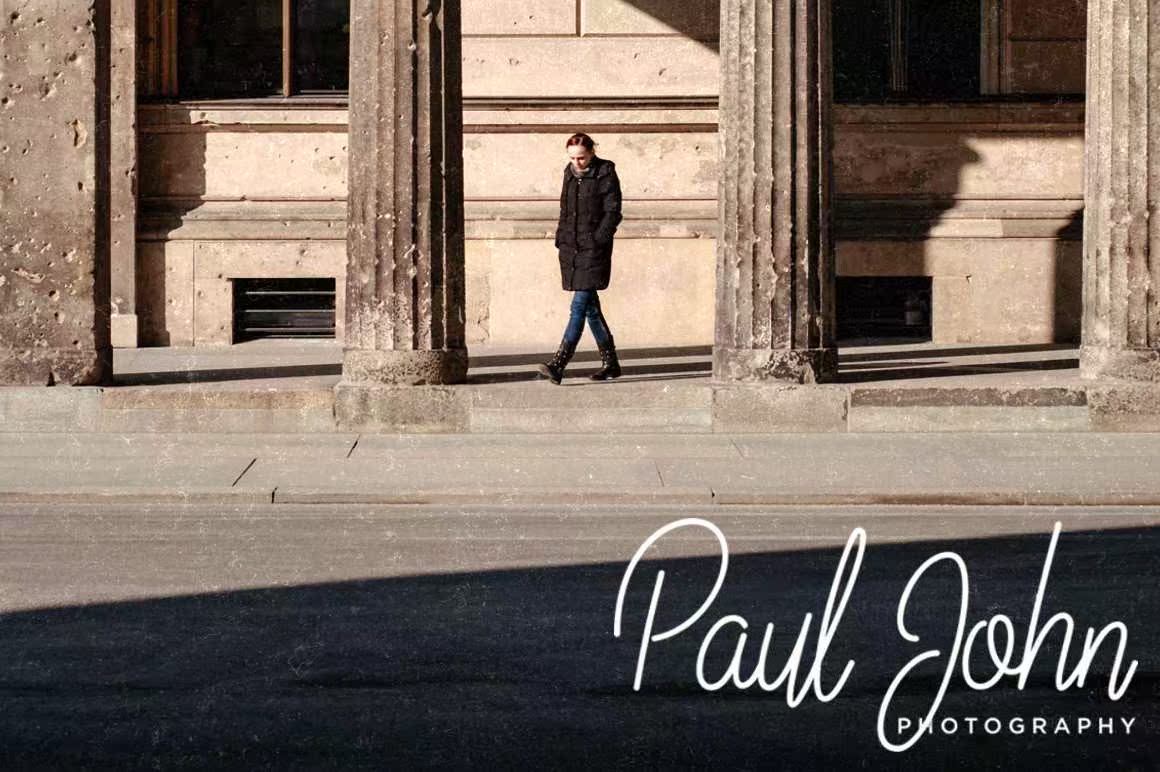
介绍最新的免费字体;LineloScript,一种受现代印刷术启发而编写的单行文字。该文字与我们的实际书写相比有很大的差距,它的基线跳动,高度不一致,有助于您获得真实的手感。适合您设计的任何项目;婚庆活动、冒险的时髦时装报价人、t恤设计、定制排版、fauxneonsign、younameit。简介最新免费字体;LineloScript,一种受现代印刷术启发而编写的单行文字。该文字与我们的实际书写相比有很大的差距,它的基线跳动,高度不一致,有助于您获得真实的手感。适合您设计的任何项目;婚礼庆典、大胆的时髦时装报价人、t恤设计、定制排版、fauxneonsign、younameit。